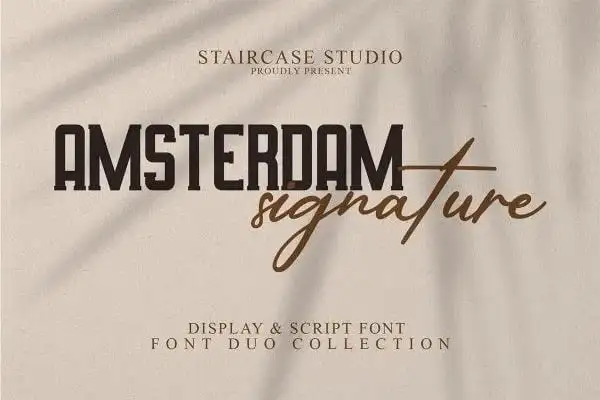
Amsterdam Font Duo – Download Grátis
A Amsterdam Font Duo é uma seleção de fontes para scrapbooking que adicionará um toque acolhedor e alegre a qualquer projeto. Inspirado pelo seu formato jovial e único, este conjunto de fontes pode ser a solução perfeita para levar suas ideias de design até o próximo nível. Com suas formas levemente ornamentadas e cores vibrantes, essas fontes se destacam como uma opção irresistível para quem deseja trazer um toque pessoal e criativo aos seus projetos de scrapbooking. Ideal tanto para a criação de cartões personalizados quanto para adicionar um toque especial a suas páginas de memórias, as Amsterdam Font Duo não apenas oferecem um grande nível de detalhe, mas também uma sensação acolhedora que certamente fará seu trabalho.